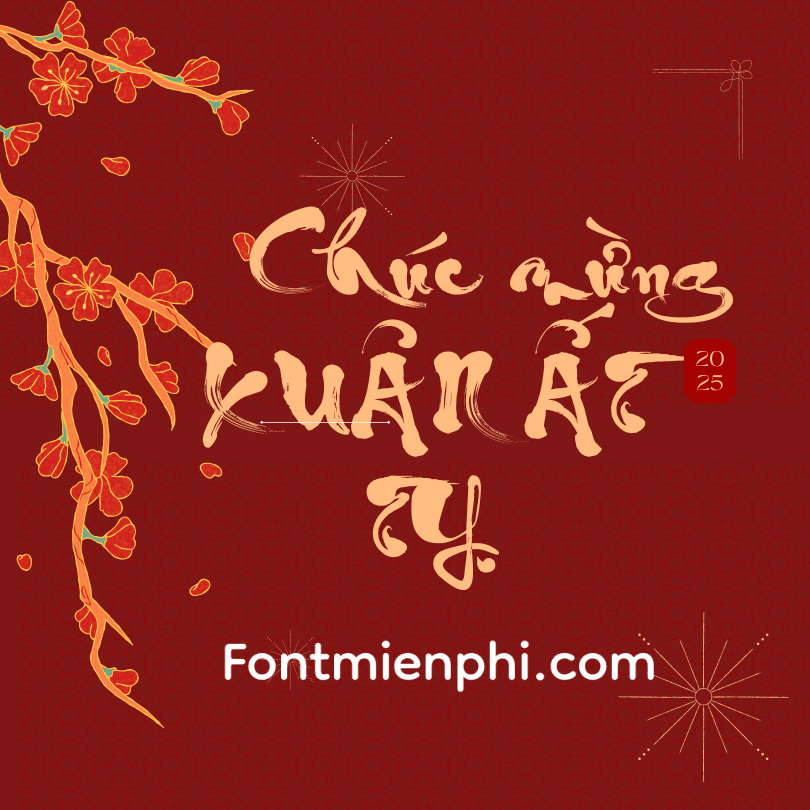
Font thư pháp Công Thuỷ ,font Tết
Bộ phông chữ tương thích với nhiều thiết bị và hệ điều hành như Windows, macOS, Linux. Thư Pháp Công Thủy Font của Trịnh Văn Công với những đường nét độc đáo sẽ thêm lựa chọn tuyệt vời cho mọi người. Tác giả Font Thư pháp Công Thủy là nhà thiết kế Trịnh Văn Công, một người rất yêu loại hình nghệ thuật này. Mục đích của anh lúc đầu muốn thỏa niềm đam mê, sau đó đã chia sẻ cho mọi người dùng và may mắn được đón nhận nhiệt tình.
Font thư pháp Công Thủy và Font Tết
Font thư pháp Công Thủy
Font thư pháp Công Thủy là một kiểu chữ mang đậm ảnh hưởng của nghệ thuật thư pháp truyền thống Việt Nam. Thiết kế của font này thường có những nét uốn lượn mềm mại, mang lại cảm giác nhẹ nhàng và bay bổng. Các chữ cái trong font đều được viết với độ dày mỏng khác nhau, tạo nên sự hài hòa và cân đối. Font này thường được sử dụng trong các tác phẩm nghệ thuật, thiệp mời, và các sự kiện văn hóa nhằm tạo ra không khí trang trọng và đẹp mắt.
Font Tết
Font Tết là kiểu chữ được thiết kế đặc biệt để phù hợp với không khí lễ hội Tết Nguyên Đán. Với những họa tiết trang trí phong phú, những nét chữ vui tươi và màu sắc rực rỡ, font này thường được sử dụng cho các sản phẩm quảng cáo, thiệp chúc Tết, và trang trí trong dịp lễ. Font Tết thường mang lại cảm giác vui vẻ, ấm áp và hạnh phúc, phản ánh tinh thần của ngày Tết cổ truyền Việt Nam.
Cả hai font này đều có giá trị nghệ thuật cao và được yêu thích trong việc thể hiện văn hóa và truyền thống Việt Nam.